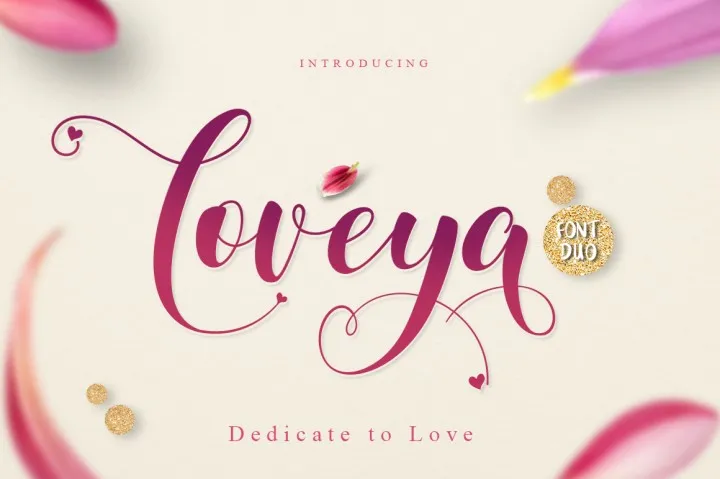
Loveya Script Font – Fonte Grátis
Loveya Script Font
Introduzimos a fonte Loveya Script! Desenhada por Khurasan, esta é uma fonte premium disponível no Thehungryjpeg, mas está disponível gratuitamente hoje para download. Loveya Script é uma linda fonte de estilo script, com influência de caligrafia moderna e tipo fresco. Este elegante estilo brush font seria perfeito para um design variado como logomarca, marca, convite, cartão de agradecimento, assinatura ou até mesmo painéis publicitários. É uma ótima opção se você está buscando um recurso gráfico que possa adicionar um toque único e sofisticado aos seus projetos visuais. Seja para a sua marca pessoal ou profissional, Loveya Script certamente encaixará perfeitamente no seu design.